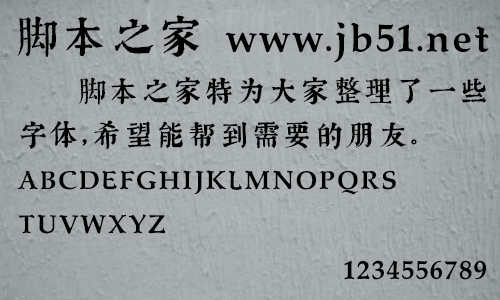
喜鵲古字典簡體regular是一款由喜鵲造字開發(fā)的一款中文字體,這款字體筆觸較為粗實,字形莊重 細節(jié)有力。制作數(shù)字字形時 追求還原古籍原味,保留描摹時的斑駁輪廓而成,適合應用于藝術設計、平面宣傳設計、網(wǎng)頁設計、書法字帖等領域,需要的朋友可以前來本站下載
適用于排版古典詩詞,武俠小說,古風文創(chuàng),傳統(tǒng)美食,古裝影視劇等。
符合GB 2312標準6763個簡體漢字外加580個繁體字形,配有相應風格的英文以及標點